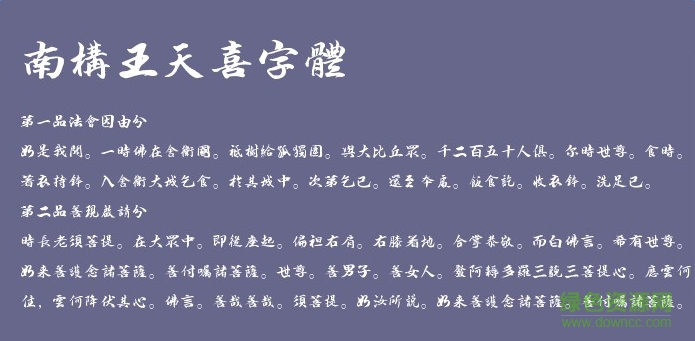
南構(gòu)王天喜體
南構(gòu)王天喜字體是一款南構(gòu)類行書(shū)風(fēng)格字體軟件,由著名書(shū)法家王天喜傾心創(chuàng)作而成,字體飄逸卻又不失工整,整體效果得體大方,非常耐看,感興趣的朋友歡迎來(lái)綠色資源網(wǎng)下載體驗(yàn)!
字體介紹
南構(gòu)王天喜字體由王天喜先生書(shū)寫(xiě)字型的一款行書(shū)字體,王天喜,浙江省江山市峽口鎮(zhèn)人,自幼酷愛(ài)書(shū)法,在繁忙的事業(yè)中不忘筆耕,其書(shū)博古通今,顧盼生輝,這是一款具有儒雅中國(guó)風(fēng)的行書(shū)字體。